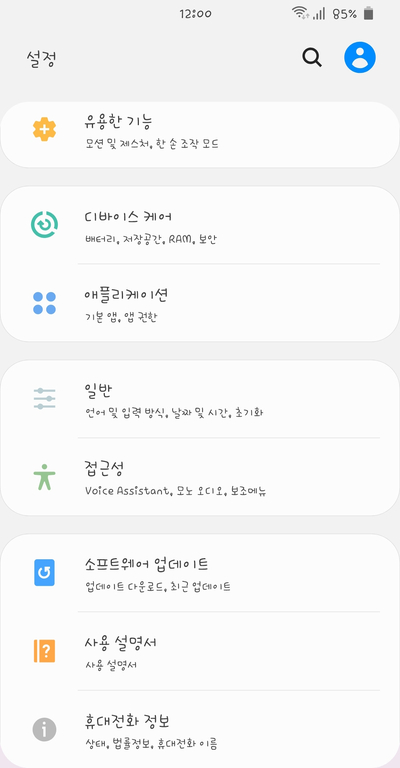
마니또
갤럭시스토어에서 제공되는 365마니또 폰트는 사용자들에게 따뜻하고 친근한 느낌을 전달하는 특별한 UI 폰트입니다. 이 폰트의 주요 특징을 살펴볼게요.
디자인 특징
글자의 부드러운 곡선이 따뜻한 마음을 전달합니다. '마니또'라는 이름에서 알 수 있듯이, 수호천사와 같은 친근하고 도움을 주는 이미지를 연상시킵니다.
특수 문자 기능
365마니또 폰트는 일반적인 문자 외에도 특별한 이모티콘과 심볼을 제공합니다.
;) 입력 시 예쁜 선물 상자 표시
;> 입력 시 귀여운 표정 1 표시
:!: 입력 시 귀여운 표정 2 표시
:?: 입력 시 귀여운 표정 3 표시
:;: 입력 시 사랑의 쪽지 표시
추가 기능
기본 키보드에 없는 특수 문자는 인터넷 검색창에서 복사 후 메모장이나 클립보드에 저장해 놓고 필요할 때 사용할 수 있습니다. 365마니또 폰트는 사용자의 디바이스에 따뜻함과 개성을 더해주는 동시에, 재미있는 특수 문자 기능으로 메시지나 SNS 사용 시 더욱 풍부한 표현을 가능하게 해줍니다.
폰트 적용후 어떻게 보이나요?
마니또 폰트를 적용하면 어떻게 보이는지 궁금하시죠? 아래의 이미지로 폰트의 모양을 확인하여 볼 수 있습니다.